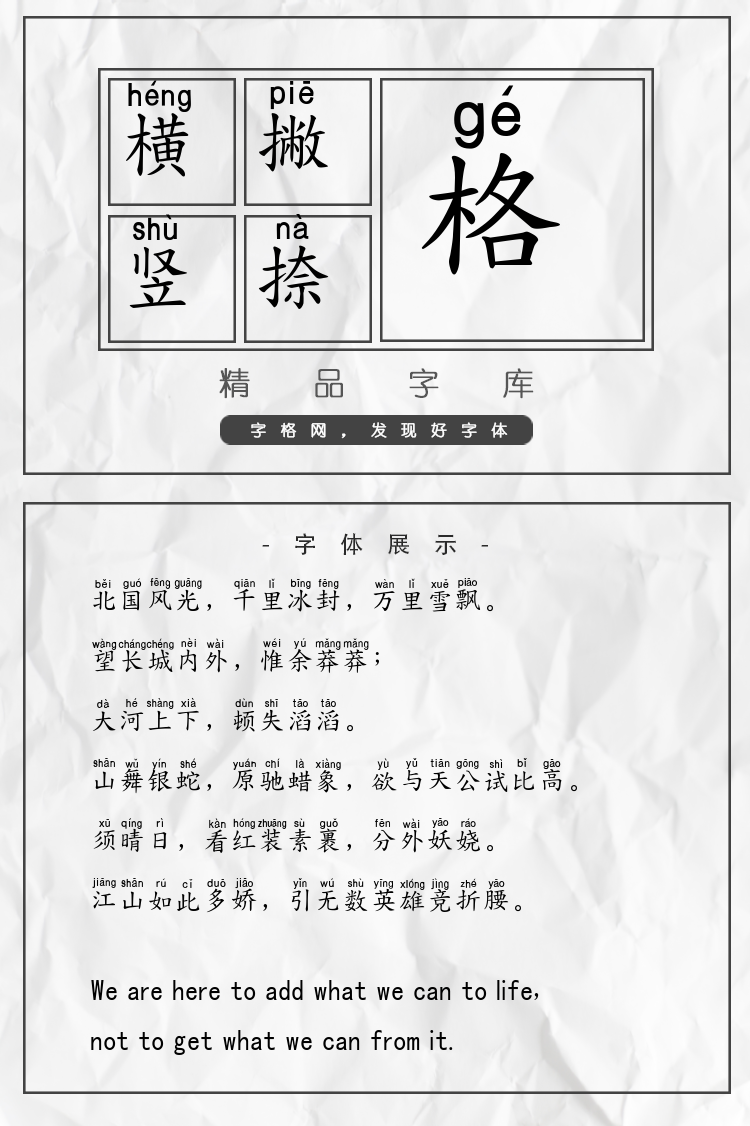
也字工厂教科书拼音体
字体说明:也字工厂教科书拼音体字体是一款可商用的毛笔书法,英文手写,手写体字体,该字体包含6763个中文、字母、符号和数字,具有充满力量、大气、豪放、稳重、手写风、古典 的风格,可以满足您设计上的各种需求,该字体主要用于电商、广告、视频影视、海报企宣、书籍 等场景, 您不但可以在字格网下载也字工厂教科书拼音体,同时还有众多毛笔书法字体、创意字体等可供选择!